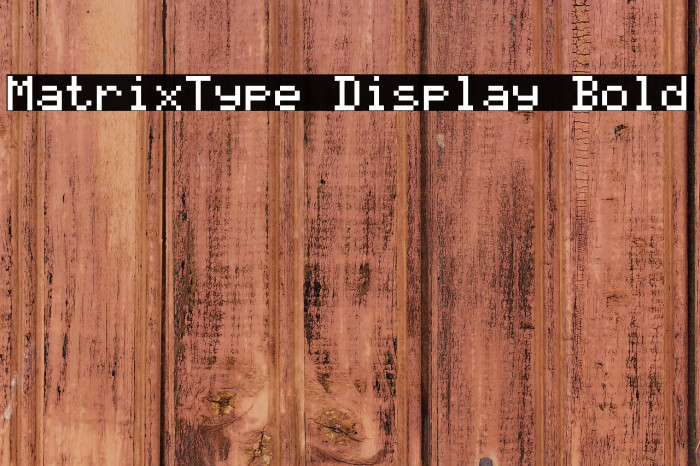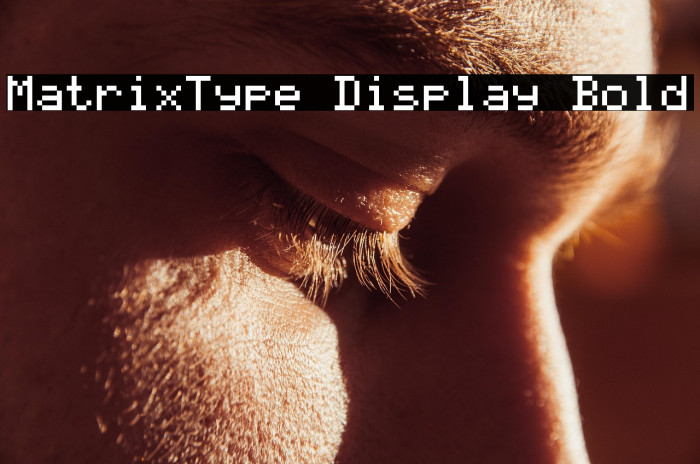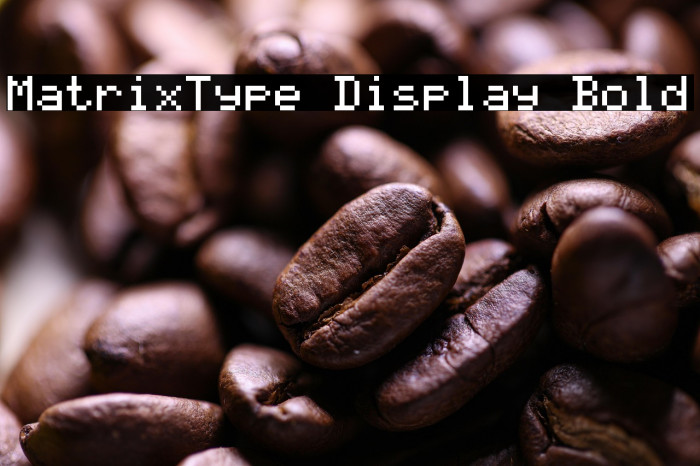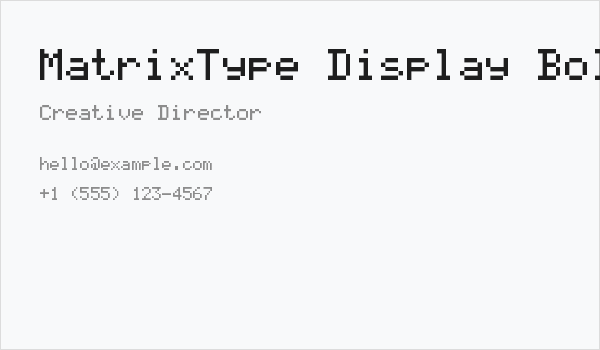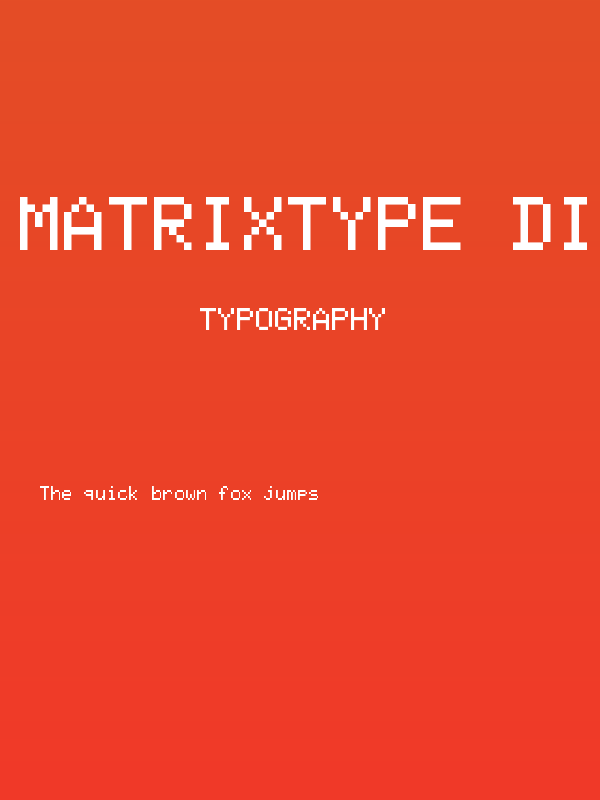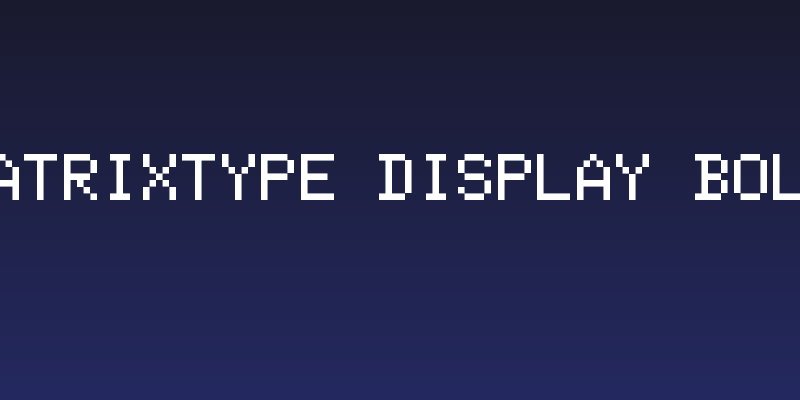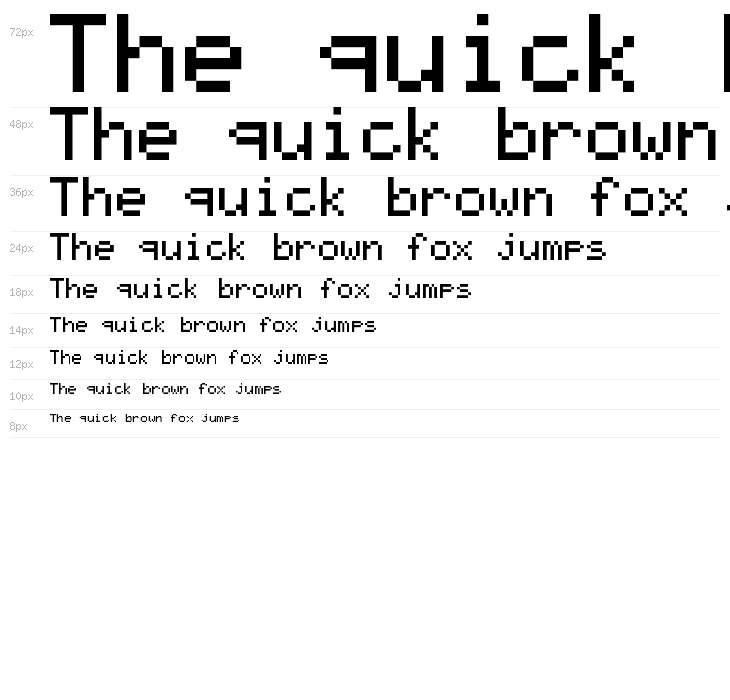
MatrixType Display Bold Font
✎ Pixel
| Categorie | Pixel |
| Caso d'uso | Logos, Headlines, Digital Art |
| Progetti proposti | Ideal for retro video game designs, digital art projects, tech-themed posters, and any creative work that seeks a vintage digital look. |